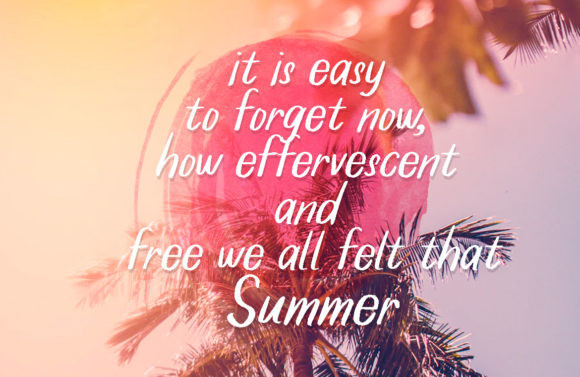
Creativefabrica Mojito Font
[Creativefabrica] Mojito Font
Мохито - милый рукописный шрифт.
Его сладкий и полный жизни стиль делает этот шрифт прекрасным выбором для осветления ваших конструкций.